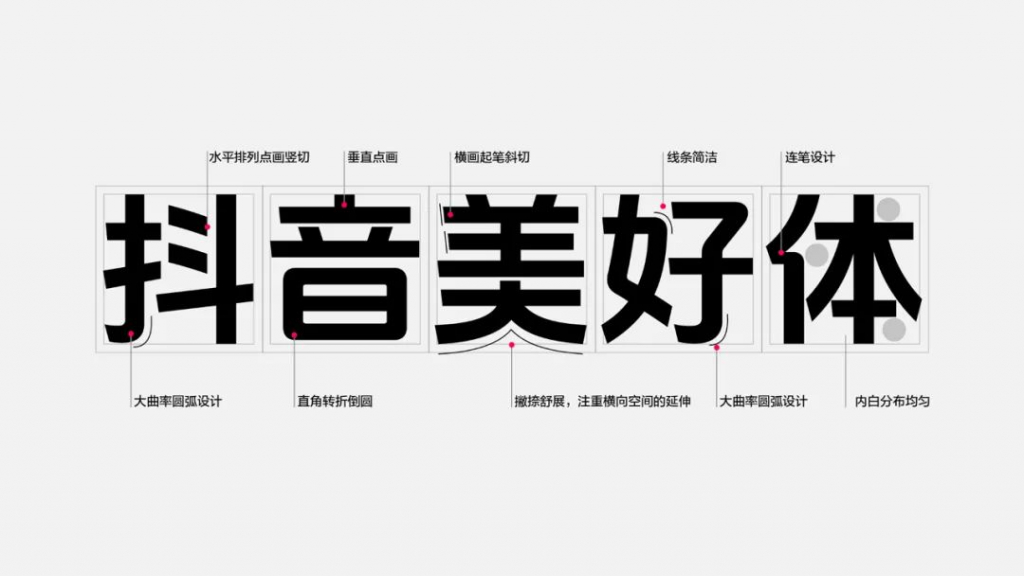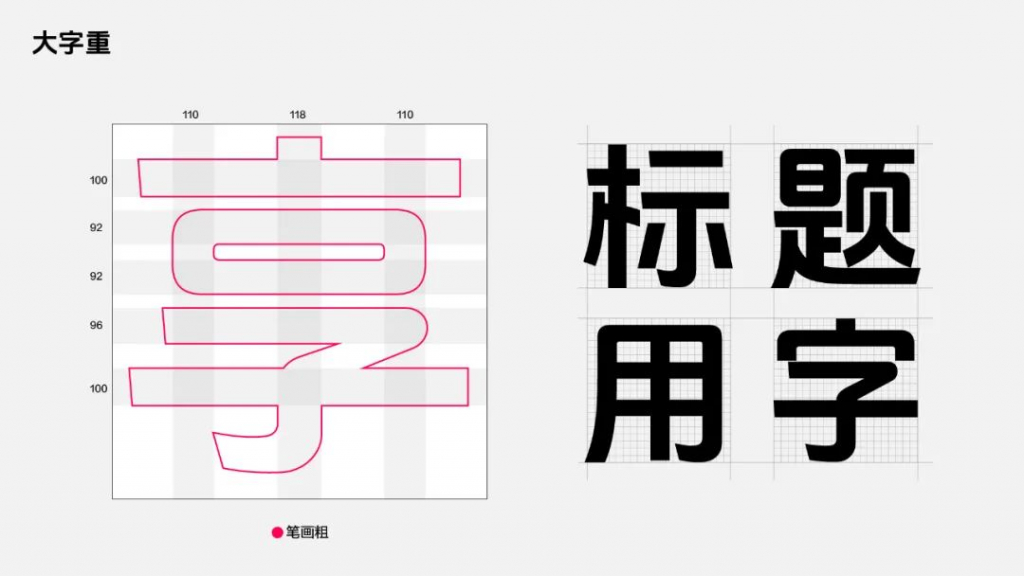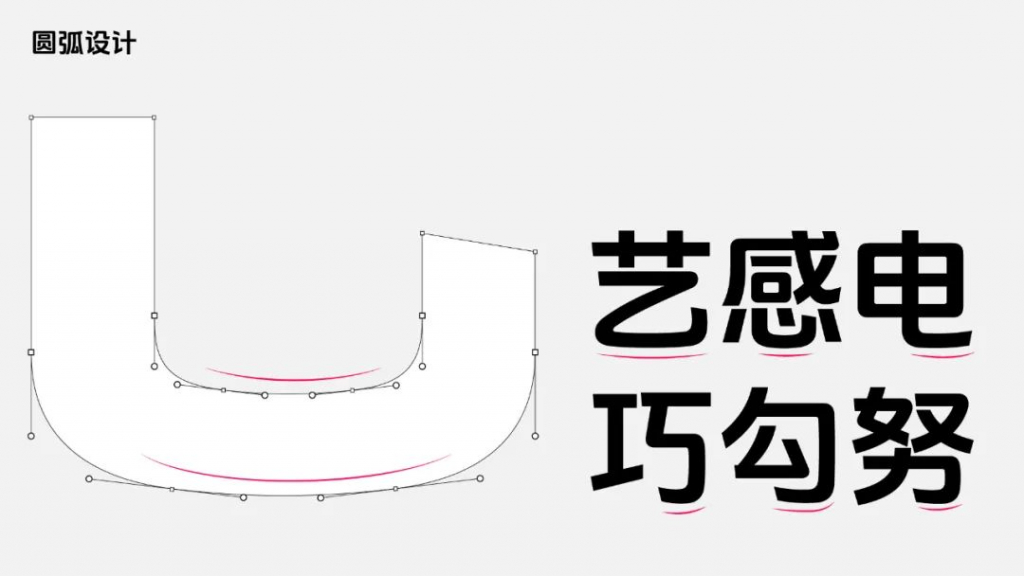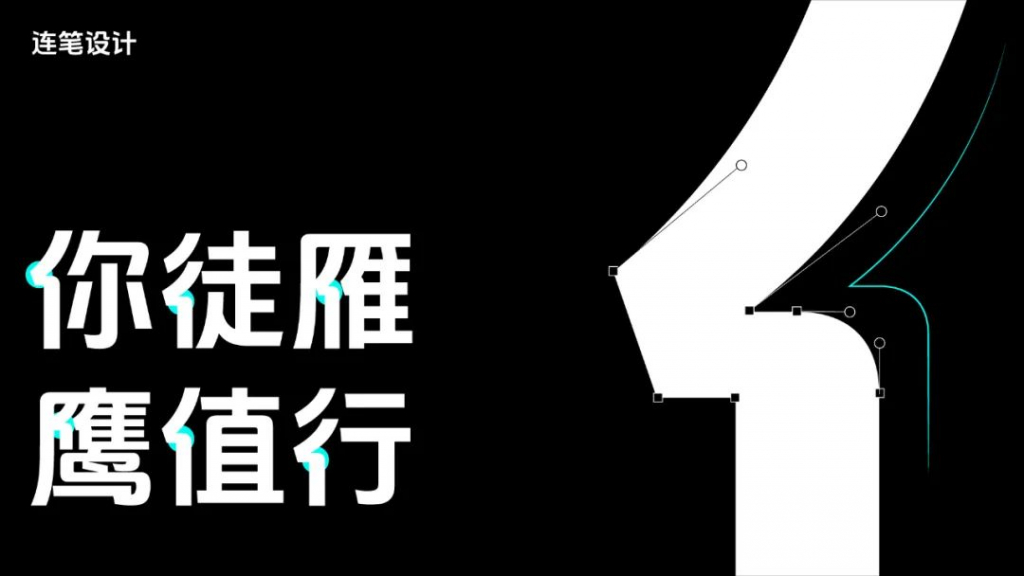
抖音美好体
2023年,抖音已经从短视频平台发展为多体裁内容创作与分享平台,将优质内容带给用户的同时,更鼓励每一个人轻松创作与分享,去发现美好、传递美好。为了更好地传播“记录美好生活”的品牌理念,更好地满足品牌长远发展,打造优质的内容创作与产品体验,抖音体验设计中心与方正字库联合设计开发了一款简洁大方、清晰易读,同时兼具现代气质与人文属性的品牌定制字体——抖音美好体。
抖音美好体包含6763个中文字符,682个西文及数字符号,执行国家GB2312-80简体中文编码字符标准。作为品牌标准字体,抖音美好体将会率先用于抖音及其子品牌中,助力品牌视觉形象的统一,提升品牌的官方性、权威感。